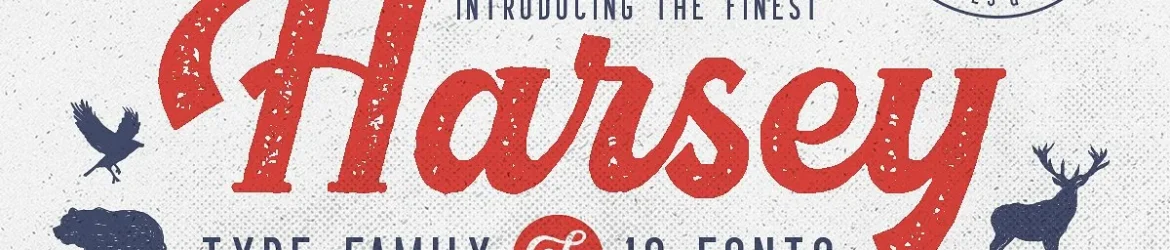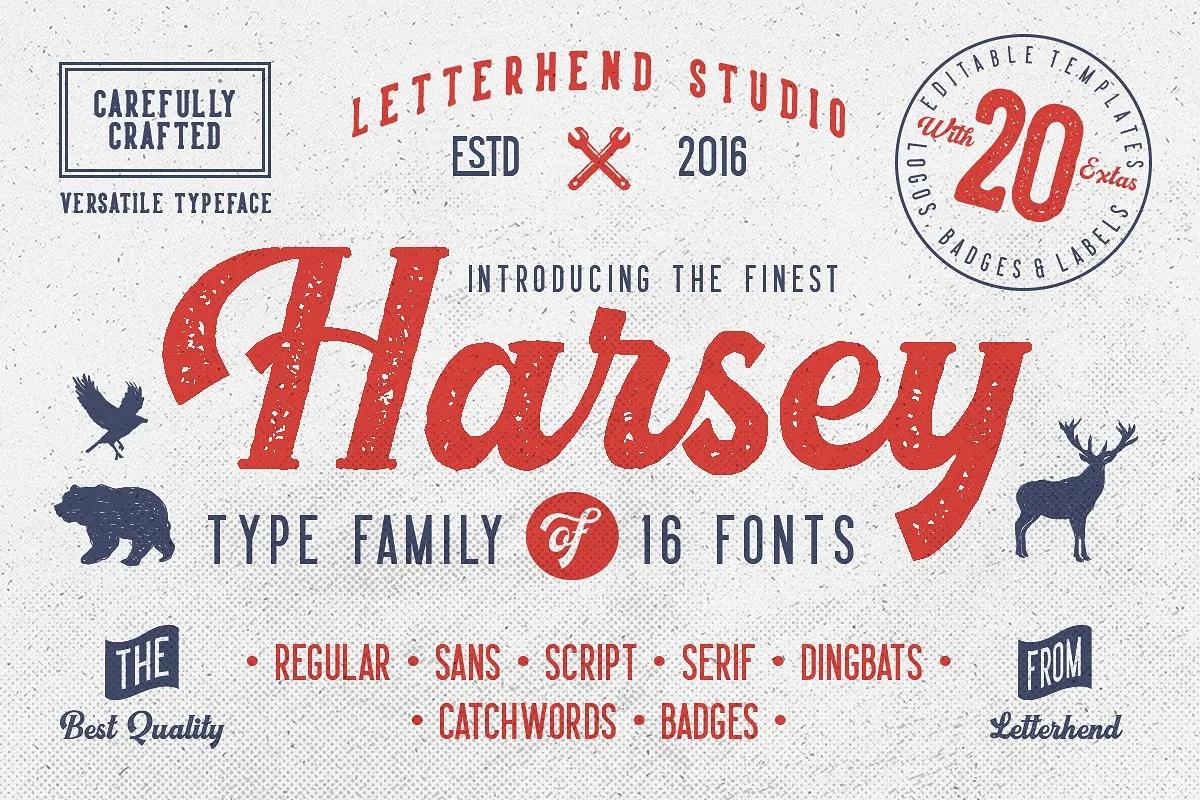
Harsey Typeface
A Harsey Typeface é uma família de 16 tipografias que transmite um sentimento nostálgico e vintage. Seu design antigo e retro cumpre diversas funções, adequado para ambientes variados – desde aplicativos até camisetas personalizadas ou designs gráficos. Nesta coleção exclusiva chamada Harsey Type ToolBox você encontrará uma variedade de estilos, como script, sans-serif, serif, além de elementos decorativos como dingbat, catchwords e badges, todos em formato de fonte. Um destaque especial é a inclusão de 20 identidades premoldadas, cada uma deles editável para que você possa personalizar as letras ao seu gosto instantaneamente. O produto ainda oferece a vantagem única de combinar perfeitamente todas essas tipografias juntas. Seja você um designer gráfico ou criativo de marketing, o Harsey Typeface pode ajudar você a dar vida à sua ideia com estilo e sofisticação.